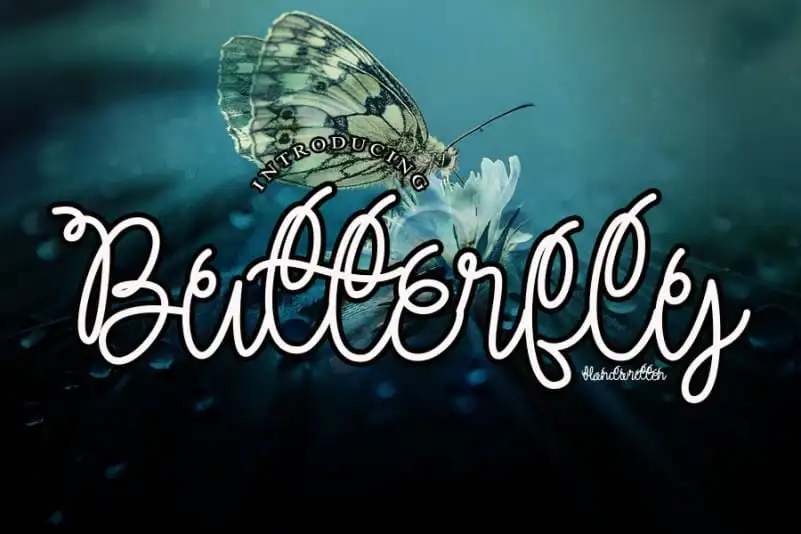
Butterfly Handwritten Font – Fonte Grátis
Butterfly Handwritten Font
A Butterfly Handwritten Font é uma elegante escolha para quem busca estilo único em design editorial ou tipográfico. Desenvolvida pelo designer LevinCreative, essa fonte casual e fina traz um toque de suavidade que se assemelha a uma caligrafia realista. Ideal tanto para criações simples quanto para projetos mais elaborados, esta fonte atende ao maior leque possível, enriquecendo seus design com uma personalidade única e vibrante. Seja em cartazes ou gráficos web, o Butterfly Handwritten Font transforma qualquer projeto em um verdadeiro trabalho de arte, elevando-o a um novo patamar. É perfeito para designers que valorizam estilo e elegância no mesmo momento.